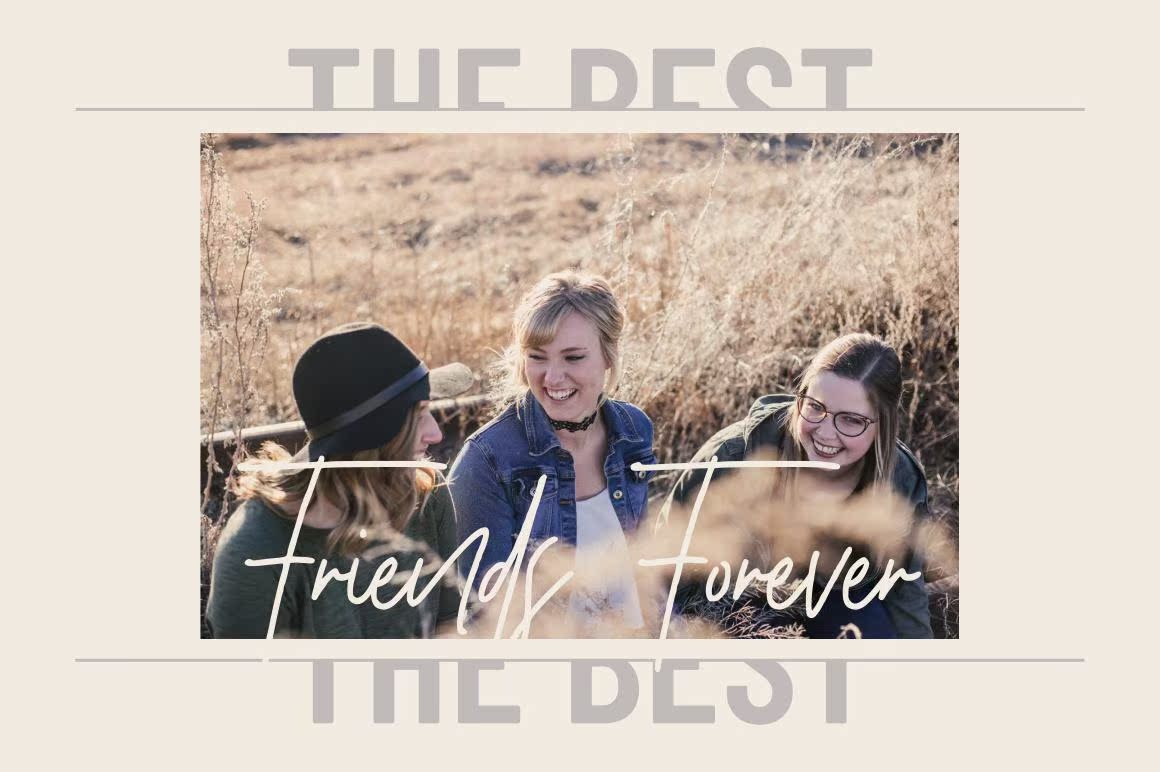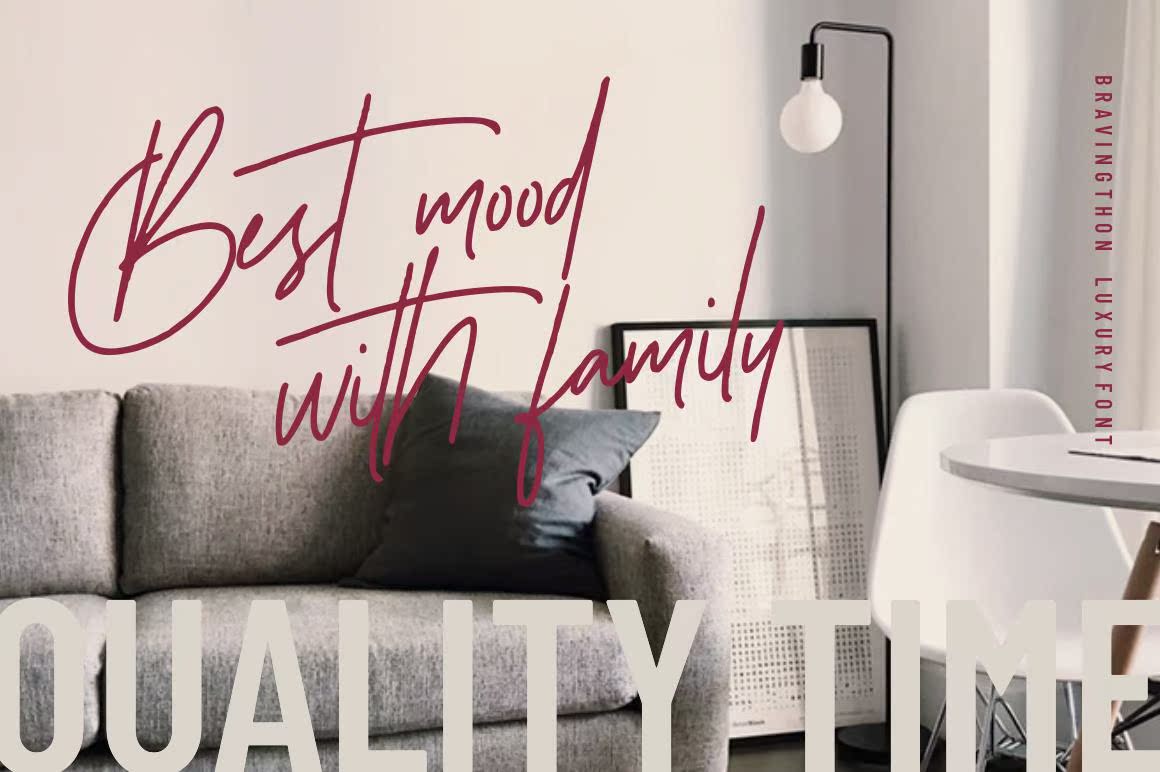
Bravingthon–针对自然和现代的随意签名和书写字体。我非常适合于徽标、邀请、文具、婚礼设计、社交媒体、广告、产品包装、产品设计、标签、照片、水印、特殊物品或任何东西。此字体包括:Bravingthon notf TTF WOFF、连字带、,以及多种语言支持。Bravingthon–针对自然和现代的随意签名和书写字体。我非常适合于徽标、邀请函、文具、婚礼设计、社交媒体、广告、产品包装、产品设计、标签、摄影、水印、特殊品或任何东西。此字体包括:不含TTF WOFF的Bravingthon、连字和多种语言支持。